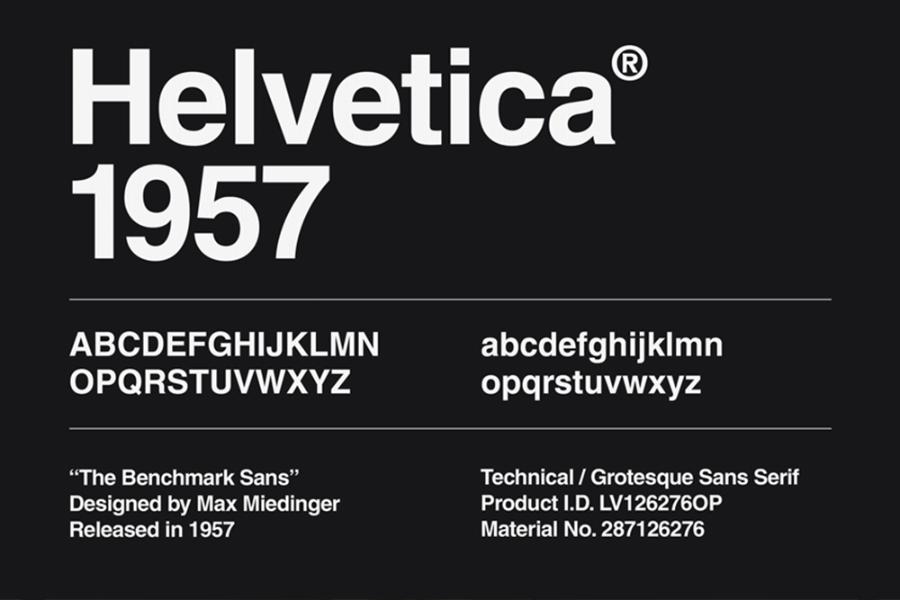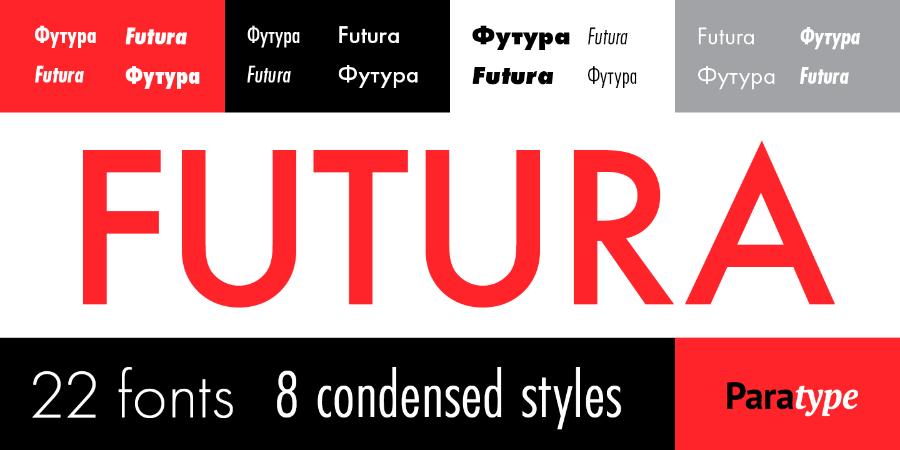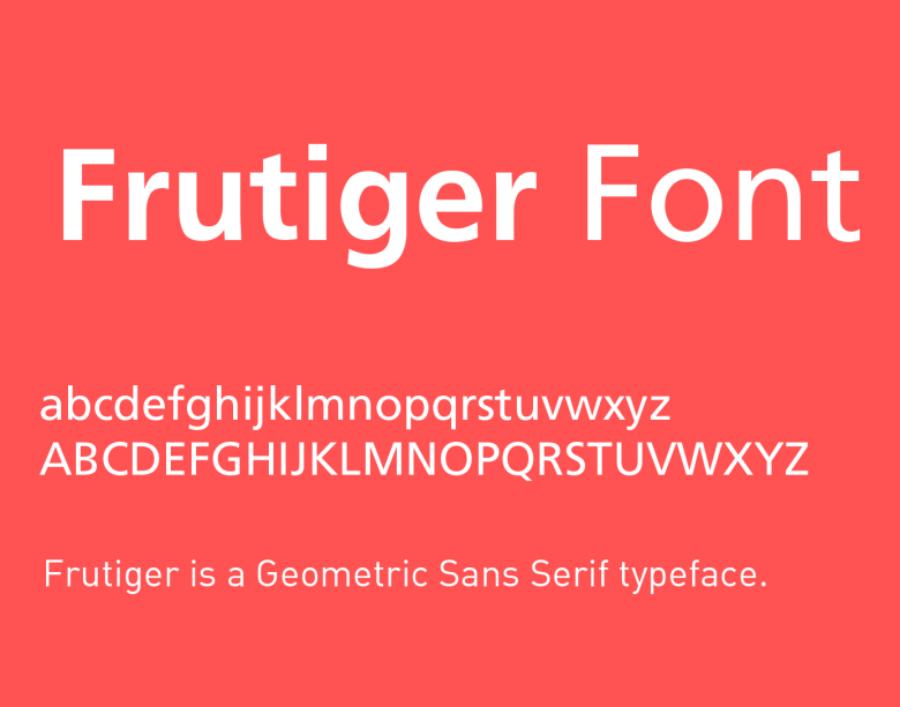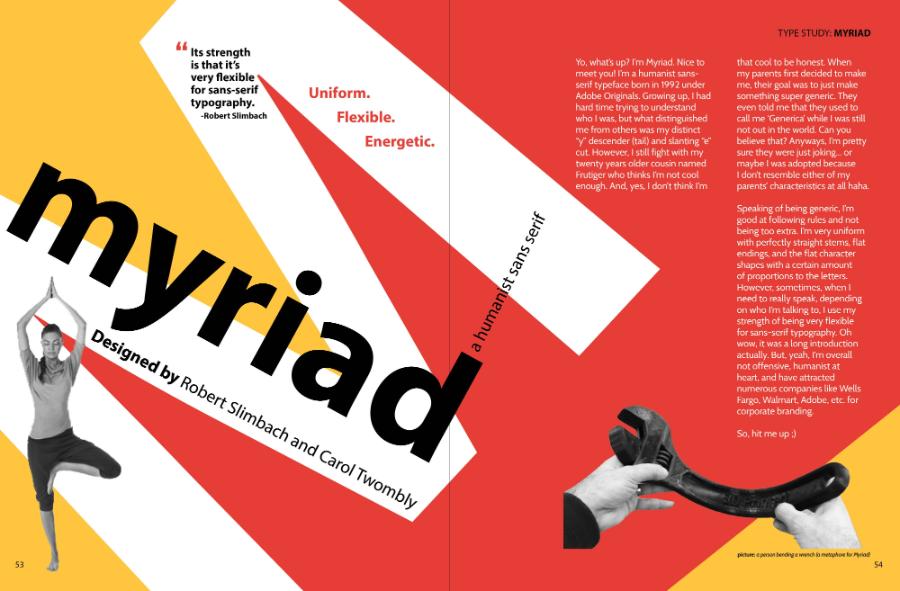
10 Font Chữ Kinh Điển Mọi Designer Không Thể Bỏ Qua
Khám phá 10 font chữ kinh điển mà mọi designer nên biết. Những kiểu chữ này không chỉ mang tính biểu tượng mà còn giúp bạn nâng cao hiệu quả thiết kế và tạo dấu ấn cá nhân
10 Font Chữ Kinh Điển Mọi Designer Không Thể Bỏ Qua
Font chữ là linh hồn của mọi thiết kế. Một lựa chọn đúng không chỉ nâng tầm thẩm mỹ mà còn truyền tải được cá tính và thông điệp thương hiệu. Trong vô vàn lựa chọn, có những cái tên đã vượt qua thời gian, trở thành “kinh điển” và không thể thiếu trong kho tàng của bất kỳ nhà thiết kế nào. Bài viết dưới đây sadesign sẽ giới thiệu 10 font chữ huyền thoại mà mọi designer, dù chuyên nghiệp hay mới bắt đầu, đều nên nắm vững.
1.Vì Sao Font Chữ Là Yếu Tố Cốt Lõi Trong Thiết Kế
Font chữ không chỉ đơn thuần là phương tiện để truyền đạt ngôn ngữ. Mỗi kiểu chữ là một hình thái thị giác, góp phần định hình nhận thức, cảm xúc và trải nghiệm của người xem. Sự phối hợp hài hòa giữa font và các yếu tố khác như màu sắc, bố cục, hình ảnh sẽ tạo nên một bản thiết kế có chiều sâu, dễ nhớ và thuyết phục.
Việc sử dụng các font chữ kinh điển không chỉ mang lại sự tinh tế, mà còn đảm bảo tính chuyên nghiệp, dễ đọc và dễ nhận diện. Những font này đã được kiểm chứng qua thời gian, sử dụng trong hàng ngàn dự án lớn nhỏ từ in ấn đến digital.
Lịch sử phát triển của font chữ song hành với sự phát triển của công nghệ in ấn và sau này là công nghệ số. Từ những chữ cái được khắc thủ công trên đá, đến những bộ chữ được đúc bằng kim loại cho máy in, và giờ đây là hàng triệu font chữ số có sẵn trên máy tính, mỗi giai đoạn đều đánh dấu một bước tiến quan trọng trong việc truyền tải thông tin và nghệ thuật. Sự quan trọng của font chữ trong thiết kế không chỉ nằm ở khả năng hiển thị văn bản rõ ràng mà còn ở khả năng tạo ra một trải nghiệm thị giác độc đáo. Một nhà thiết kế tài năng luôn biết cách khai thác tối đa sức mạnh của font chữ để truyền tải thông điệp một cách hiệu quả nhất.
Khi chọn font chữ, các nhà thiết kế cần cân nhắc nhiều yếu tố: đối tượng khán giả, mục tiêu của dự án, phong cách tổng thể và khả năng đọc. Một font chữ tuyệt đẹp nhưng khó đọc sẽ không thể phát huy hiệu quả. Ngược lại, một font chữ đơn giản nhưng dễ đọc có thể trở thành lựa chọn lý tưởng cho các tài liệu dài hoặc giao diện người dùng. Việc hiểu rõ các loại font chữ, đặc điểm và ứng dụng của chúng là nền tảng vững chắc cho bất kỳ ai muốn thành công trong lĩnh vực thiết kế.
2.Tiêu Chí Lựa Chọn Font Chữ Kinh Điển
Để một font chữ trở thành "kinh điển", nó phải vượt qua những tiêu chí khắt khe về thời gian và ứng dụng. Không phải font nào cũng có thể đạt được danh hiệu này. Những font chữ kinh điển thường sở hữu những đặc điểm chung, khiến chúng trở nên bất tử và được yêu thích qua nhiều thế hệ designer.
2.1 Tính Linh Hoạt Và Khả Năng Ứng Dụng Rộng Rãi
Một font chữ kinh điển phải có khả năng thích ứng với nhiều loại hình thiết kế khác nhau. Nó có thể được sử dụng cho tiêu đề, nội dung chính, logo, bao bì, website, ứng dụng di động, và nhiều hơn nữa. Tính linh hoạt này đến từ sự cân bằng trong thiết kế, không quá đặc trưng hay lỗi thời, cho phép nó hòa nhập tốt với các yếu tố thiết kế khác. Font chữ kinh điển không bị giới hạn bởi một phong cách hay xu hướng nhất thời. Nó có thể phù hợp với cả thiết kế hiện đại và cổ điển, tạo nên sự hài hòa và chuyên nghiệp.
2.2  Vẻ Đẹp Vượt Thời Gian
Xu hướng thiết kế liên tục thay đổi, nhưng những font chữ kinh điển vẫn giữ được vẻ đẹp và sự phù hợp. Chúng không bị lỗi thời bởi những thay đổi trong thị hiếu, mà ngược lại, luôn duy trì được sức hấp dẫn riêng. Điều này đến từ sự tinh tế trong từng đường nét, tỷ lệ cân đối và tính thẩm mỹ tổng thể. Những font chữ này được tạo ra dựa trên những nguyên tắc thiết kế vững chắc, đảm bảo chúng sẽ luôn trông đẹp mắt và chuyên nghiệp, bất kể thời đại nào. Vẻ đẹp vượt thời gian là yếu tố cốt lõi giúp font chữ duy trì vị thế của mình.
2.3 Khả Năng Dễ Đọc Và Dễ Nhận Biết
Dù có vẻ đẹp đến đâu, một font chữ không thể trở thành kinh điển nếu nó khó đọc. Khả năng dễ đọc (legibility) liên quan đến sự rõ ràng của từng ký tự, trong khi khả năng dễ nhận biết (readability) liên quan đến sự dễ dàng khi đọc một đoạn văn dài. Những font chữ kinh điển luôn được thiết kế để đảm bảo sự rõ ràng tối ưu, giúp người đọc dễ dàng tiếp nhận thông tin mà không bị mỏi mắt. Điều này đặc biệt quan trọng trong các ấn phẩm in ấn, trang web và các ứng dụng nơi văn bản là thành phần chính.
3. Top 10 Font Chữ Kinh Điển Mọi Designer Đều Phải Nắm Vững
Giờ đây, chúng ta sẽ cùng khám phá 10 font chữ đã khẳng định được vị thế của mình trong lịch sử và hiện tại của ngành thiết kế. Mỗi font chữ đều có câu chuyện, đặc điểm và ứng dụng riêng biệt, tạo nên sức hút khó cưỡng.
3.1. Helvetica: Biểu Tượng Của Chủ Nghĩa Hiện Đại
• Lịch sử và Ra đời: Helvetica, ra mắt vào năm 1957 bởi Max Miedinger và Eduard Hoffmann tại Thụy Sĩ, ban đầu có tên là Neue Haas Grotesk. Tên gọi Helvetica được đặt vào năm 1960, lấy cảm hứng từ "Helvetia" - tên tiếng Latin của Thụy Sĩ. Sự ra đời của Helvetica đánh dấu một kỷ nguyên mới trong thiết kế font chữ, hướng đến sự đơn giản, rõ ràng và trung lập.
• Đặc điểm nổi bật: Helvetica thuộc nhóm font Sans-serif (không chân), với các đường nét sạch sẽ, gọn gàng, và khoảng cách giữa các ký tự được tối ưu. Điều đặc biệt ở Helvetica là sự đồng nhất trong chiều cao của các chữ cái viết thường và chiều rộng của các ký tự, tạo nên một khối văn bản cân đối và dễ đọc. Nó có rất nhiều biến thể (weights) từ Thin đến Black, phù hợp với mọi mục đích sử dụng.
• Lý do trở thành kinh điển: Tính trung lập, tính linh hoạt và khả năng dễ đọc vượt trội đã giúp Helvetica trở thành một trong những font chữ được sử dụng rộng rãi nhất trên thế giới. Nó không mang theo bất kỳ cảm xúc hay định kiến nào, cho phép nội dung tự nói lên tất cả.
• Ứng dụng phổ biến: Helvetica được sử dụng rộng rãi trong các logo thương hiệu (Jeep, Panasonic, Nestle), biển báo giao thông, hệ thống định hướng công cộng (New York City Subway), và các tài liệu của chính phủ. Nó là lựa chọn hàng đầu cho các thiết kế đòi hỏi sự rõ ràng, chuyên nghiệp và tối giản.
3.2. Garamond: Nét Đẹp Cổ Điển Tinh Tế
• Lịch sử và Ra đời: Garamond là một nhóm các kiểu chữ serif được đặt tên theo Claude Garamond, một nhà khắc chữ người Pháp sống vào thế kỷ 16. Mặc dù có nhiều phiên bản Garamond khác nhau được phát triển qua các thế kỷ, tất cả đều dựa trên những nguyên tắc thiết kế ban đầu của ông, đặc trưng bởi sự thanh lịch và tính nghệ thuật.
• Đặc điểm nổi bật: Garamond thuộc nhóm font Serif (có chân), với các chân nhỏ và đường nét uyển chuyển, tinh tế. Các ký tự của Garamond có tỷ lệ hài hòa, độ tương phản vừa phải giữa nét đậm và nét nhạt, tạo cảm giác mềm mại và dễ chịu khi đọc. Đặc trưng của Garamond là các chữ cái viết thường có chiều cao x-height (chiều cao của chữ 'x') tương đối nhỏ, mang lại cảm giác cổ điển và sang trọng.
• Lý do trở thành kinh điển: Vẻ đẹp cổ điển, sự thanh lịch và khả năng đọc tốt đã giúp Garamond trở thành lựa chọn hàng đầu cho các ấn phẩm văn học, sách báo và các tài liệu đòi hỏi tính trang trọng. Nó mang lại cảm giác uy tín và truyền thống.
• Ứng dụng phổ biến: Garamond được sử dụng rộng rãi trong xuất bản sách (sách giáo khoa, tiểu thuyết), tạp chí, và các ấn phẩm in ấn cao cấp. Nó cũng thường xuất hiện trong các thiết kế logo cho thương hiệu sang trọng, thẻ mời đám cưới và các tài liệu mang tính chất nghệ thuật.
3.3. Futura: Tiên Phong Của Chủ Nghĩa Hiện Đại
• Đặc điểm nổi bật: Futura là font Sans-serif với các đường nét thẳng, góc cạnh rõ ràng và các đường cong hoàn hảo. Các chữ cái của Futura được thiết kế dựa trên các hình khối đơn giản, tạo cảm giác mạnh mẽ, hiện đại và có tổ chức. Nó có nhiều độ dày khác nhau, từ Light đến Extra Bold, và cũng có các phiên bản condensed (nén) và extended (mở rộng).
• Lý do trở thành kinh điển: Tính hiện đại, mạnh mẽ và khả năng thích ứng với nhiều mục đích sử dụng đã giúp Futura trở thành một biểu tượng của chủ nghĩa hiện đại trong thiết kế. Nó toát lên vẻ tương lai và sự đổi mới.
• Ứng dụng phổ biến: Futura được sử dụng rộng rãi trong các logo (Volkswagen, Nike, Supreme), tiêu đề quảng cáo, áp phích phim (Gravity, Interstellar), và các tài liệu yêu cầu sự đột phá, tiên phong. NASA cũng sử dụng Futura cho các biểu tượng và tài liệu của mình.
3.4. Times New Roman: Tiêu Chuẩn Của Báo Chí Và Văn Bản
• Đặc điểm nổi bật: Times New Roman là một font Serif truyền thống, với các nét đối xứng và các chân sắc nét. Nó được tối ưu hóa để dễ đọc trên giấy in với mật độ chữ dày đặc. Font này có độ tương phản vừa phải giữa nét đậm và nét nhạt, các ký tự được thiết kế để occupying ít không gian nhất có thể mà vẫn đảm bảo độ rõ ràng.
• Lý do trở thành kinh điển: Khả năng đọc vượt trội, hiệu quả không gian và sự phổ biến rộng rãi trong ngành xuất bản đã biến Times New Roman thành một tiêu chuẩn không thể thiếu. Nó là font chữ mặc định trên nhiều hệ điều hành và phần mềm soạn thảo văn bản trong một thời gian dài.
• Ứng dụng phổ biến: Times New Roman là font chữ mặc định cho nhiều tài liệu học thuật, báo cáo, bài luận, và các ấn phẩm báo chí. Nó là lựa chọn lý tưởng cho các văn bản dài, nơi tính dễ đọc là ưu tiên hàng đầu.
3.5. Bodoni: Sự Thanh Lịch Đầy Ấn Tượng
• Đặc điểm nổi bật: Bodoni nổi bật với độ tương phản cực cao giữa nét đậm và nét nhạt, các chân mỏng và sắc nét, cùng cấu trúc hình học rõ ràng. Các đường cong của Bodoni rất tròn trịa và đối xứng, tạo cảm giác thanh lịch và sang trọng. Chiều cao x-height lớn của Bodoni giúp nó trông mạnh mẽ và hiện đại.
• Lý do trở thành kinh điển: Vẻ đẹp ấn tượng, sang trọng và kịch tính đã giúp Bodoni trở thành lựa chọn yêu thích cho các tiêu đề lớn, quảng cáo thời trang và các ấn phẩm cao cấp. Nó mang lại cảm giác quyền lực và tinh tế.
• Ứng dụng phổ biến: Bodoni thường được sử dụng trong các tạp chí thời trang (Vogue, Harper's Bazaar), quảng cáo nước hoa, trang sức, và các ấn phẩm sang trọng. Nó cũng là lựa chọn phổ biến cho logo của các thương hiệu cao cấp.
3.6. Frutiger: Sự Rõ Ràng Và Thân Thiện
• Đặc điểm nổi bật: Frutiger là font Sans-serif nhân bản (humanist sans-serif), với các đường nét rõ ràng, mở và có khoảng cách hợp lý. Nó được thiết kế để tối ưu hóa khả năng đọc trên màn hình và ở các kích thước khác nhau. Các ký tự của Frutiger có đặc điểm "nhân bản" giúp chúng trông tự nhiên và dễ tiếp cận hơn so với các font Sans-serif hình học.
• Lý do trở thành kinh điển: Khả năng đọc vượt trội, tính thân thiện và sự linh hoạt đã giúp Frutiger trở thành lựa chọn hàng đầu cho các hệ thống thông tin, giao diện người dùng và các tài liệu công cộng.
• Ứng dụng phổ biến: Frutiger được sử dụng rộng rãi trong các hệ thống biển báo (sân bay, bệnh viện), giao diện người dùng (Microsoft Windows), sách hướng dẫn, và các tài liệu yêu cầu sự rõ ràng và dễ tiếp cận.
3.7. Baskerville: Nét Đẹp Đầy Quyền Uy
• Đặc điểm nổi bật: Baskerville là font Serif với độ tương phản mạnh hơn so với các font serif cũ, các chân sắc nét và hình dáng ký tự thanh lịch. Các nét thẳng và nét cong của Baskerville được thiết kế rất cân đối, tạo cảm giác vững chãi và quyền uy. Các đường nét của Baskerville có độ tinh tế cao, mang lại vẻ sang trọng.
• Lý do trở thành kinh điển: Sự kết hợp giữa vẻ đẹp cổ điển và tính hiện đại, cùng với khả năng đọc tốt, đã giúp Baskerville trở thành lựa chọn yêu thích cho các ấn phẩm học thuật, pháp lý và các tài liệu trang trọng. Nó mang lại cảm giác đáng tin cậy và uy tín.
• Ứng dụng phổ biến: Baskerville thường được sử dụng trong các ấn phẩm sách, tài liệu pháp lý, tạp chí học thuật, và các thương hiệu muốn truyền tải sự trang trọng, truyền thống và đáng tin cậy.
3.8. Gill Sans: Sự Thanh Lịch Kiểu Anh
• Đặc điểm nổi bật: Gill Sans là font Sans-serif nhân bản, với các nét thẳng và đường cong mềm mại, tạo cảm giác thân thiện và thanh lịch. Nó có một số đặc điểm độc đáo, chẳng hạn như chữ 'a' hai tầng, chữ 'g' có móc, và chữ 'i' với dấu chấm hình vuông. Gill Sans có nhiều biến thể về độ dày, từ Ultra Light đến Extra Bold.
• Lý do trở thành kinh điển: Vẻ đẹp thanh lịch, tính linh hoạt và khả năng ứng dụng rộng rãi đã giúp Gill Sans trở thành một biểu tượng của thiết kế Anh Quốc. Nó mang lại cảm giác thân thiện nhưng vẫn rất chuyên nghiệp.
• Ứng dụng phổ biến: Gill Sans được sử dụng rộng rãi trong các logo (BBC, Monopoly), sách báo, quảng cáo, và các hệ thống biển báo (London Underground). Nó là lựa chọn phổ biến cho các thương hiệu muốn có vẻ ngoài hiện đại, nhưng vẫn giữ được nét cổ điển.
3.9. Rockwell: Sức Mạnh Của Khối Vuông
• Đặc điểm nổi bật: Rockwell có các chân serif hình khối rất dày và vuông vắn, cùng với các nét có độ đậm gần như đồng nhất. Điều này tạo cho font chữ một vẻ ngoài mạnh mẽ, vững chắc và đáng tin cậy. Nó là một trong những font Slab Serif có ảnh hưởng nhất, mang lại cảm giác công nghiệp và vững chãi.
• Lý do trở thành kinh điển: Sự mạnh mẽ, đáng tin cậy và tính linh hoạt trong thiết kế tiêu đề đã giúp Rockwell trở thành lựa chọn phổ biến cho các ấn phẩm quảng cáo, logo và các dự án đòi hỏi sự chú ý.
• Ứng dụng phổ biến: Rockwell thường được sử dụng trong các tiêu đề quảng cáo, logo (Absolut Vodka, Blockbuster), poster, và các thiết kế có tính chất mạnh mẽ, gây ấn tượng.
3.10. Georgia: Sức Mạnh Của Web Font
• Đặc điểm nổi bật: Georgia là font Serif với chiều cao x-height lớn, các đường nét rõ ràng và độ tương phản vừa phải. Các ký tự của Georgia được thiết kế để dễ đọc ngay cả ở độ phân giải thấp, giúp văn bản trên màn hình trở nên rõ ràng và dễ tiếp cận. Nó có các nét serif mạnh mẽ, giúp phân biệt các ký tự và tăng cường khả năng đọc.
• Lý do trở thành kinh điển: Khả năng đọc vượt trội trên màn hình máy tính và sự phổ biến rộng rãi trên web đã giúp Georgia trở thành một trong những web font quan trọng nhất.
• Ứng dụng phổ biến: Georgia được sử dụng rộng rãi trong các trang web, blog, ứng dụng đọc sách điện tử, và các tài liệu kỹ thuật số. Nó là lựa chọn lý tưởng cho các văn bản dài trên môi trường online.
Kho Font Chữ Đẹp
4. Kết bài
Hành trình khám phá 10 font chữ kinh điển mà mọi designer đều phải biết đã khép lại. Từ sự trung lập đầy quyền năng của Helvetica đến vẻ đẹp cổ điển của Garamond, sự tiên phong của Futura hay tính hữu dụng của Times New Roman, mỗi font chữ đều mang trong mình một câu chuyện, một sứ mệnh riêng. Việc nắm vững lịch sử, đặc điểm và ứng dụng của những font chữ này không chỉ giúp bạn nâng cao kỹ năng thiết kế mà còn mở ra cánh cửa đến một thế giới sáng tạo không giới hạn.